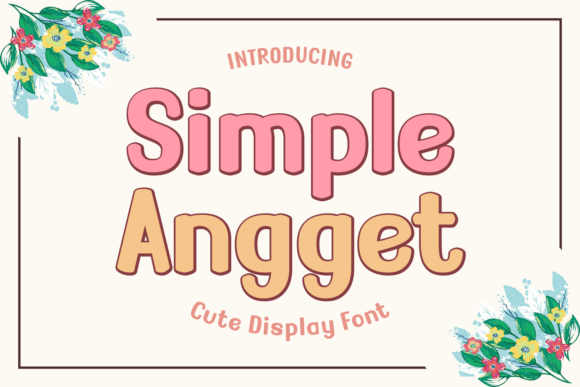
Simple Angget
Simple Anggetのような高品質の素材をお探しの場合、このプレミアムパッケージはクリエイティブなプロジェクトに素晴らしい選択です。
POD(オンデマンド印刷)製品、結婚式の招待状、またはソーシャルメディアのグラフィックを作成している場合でも、Simple Anggetは理想的です。